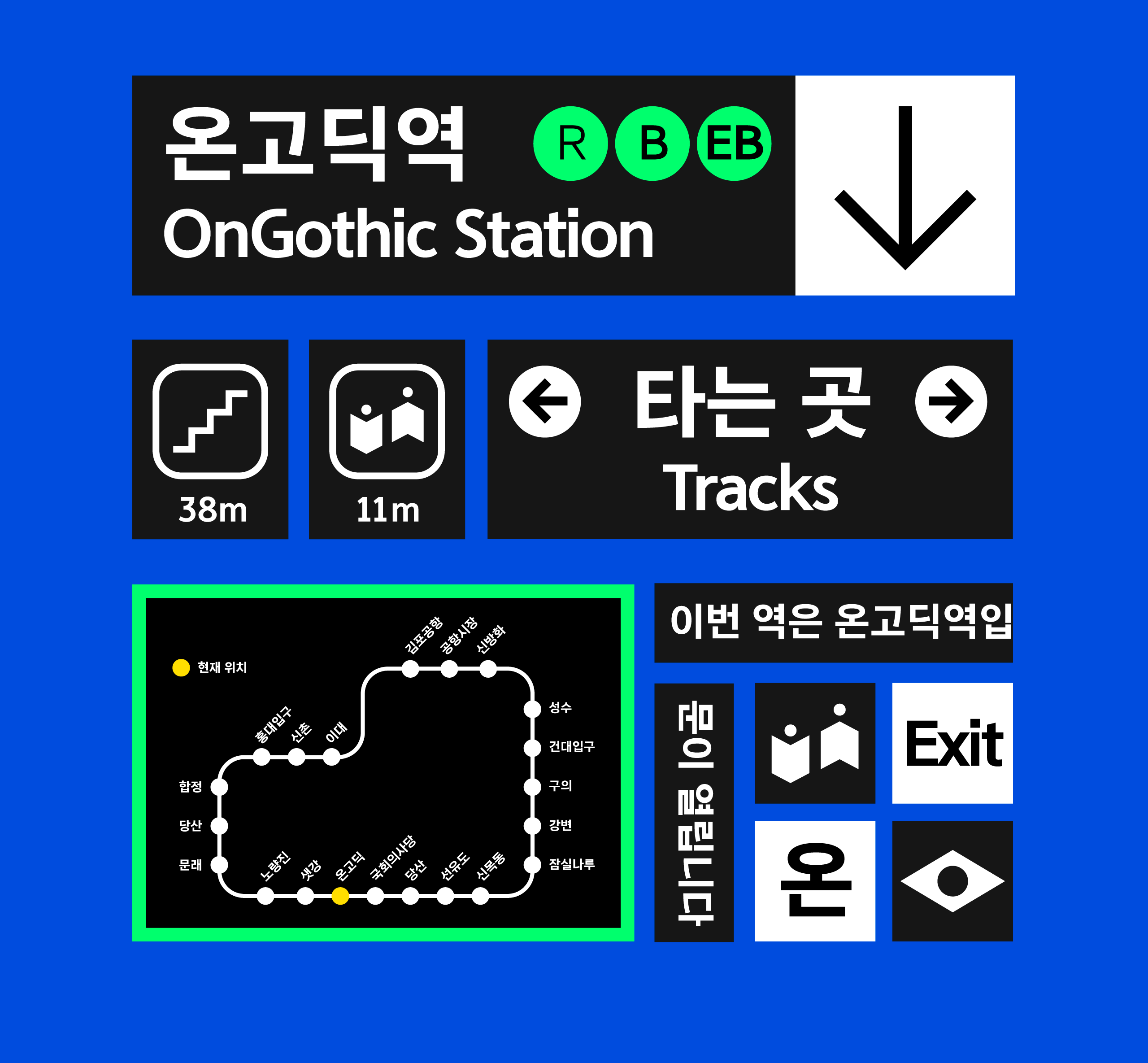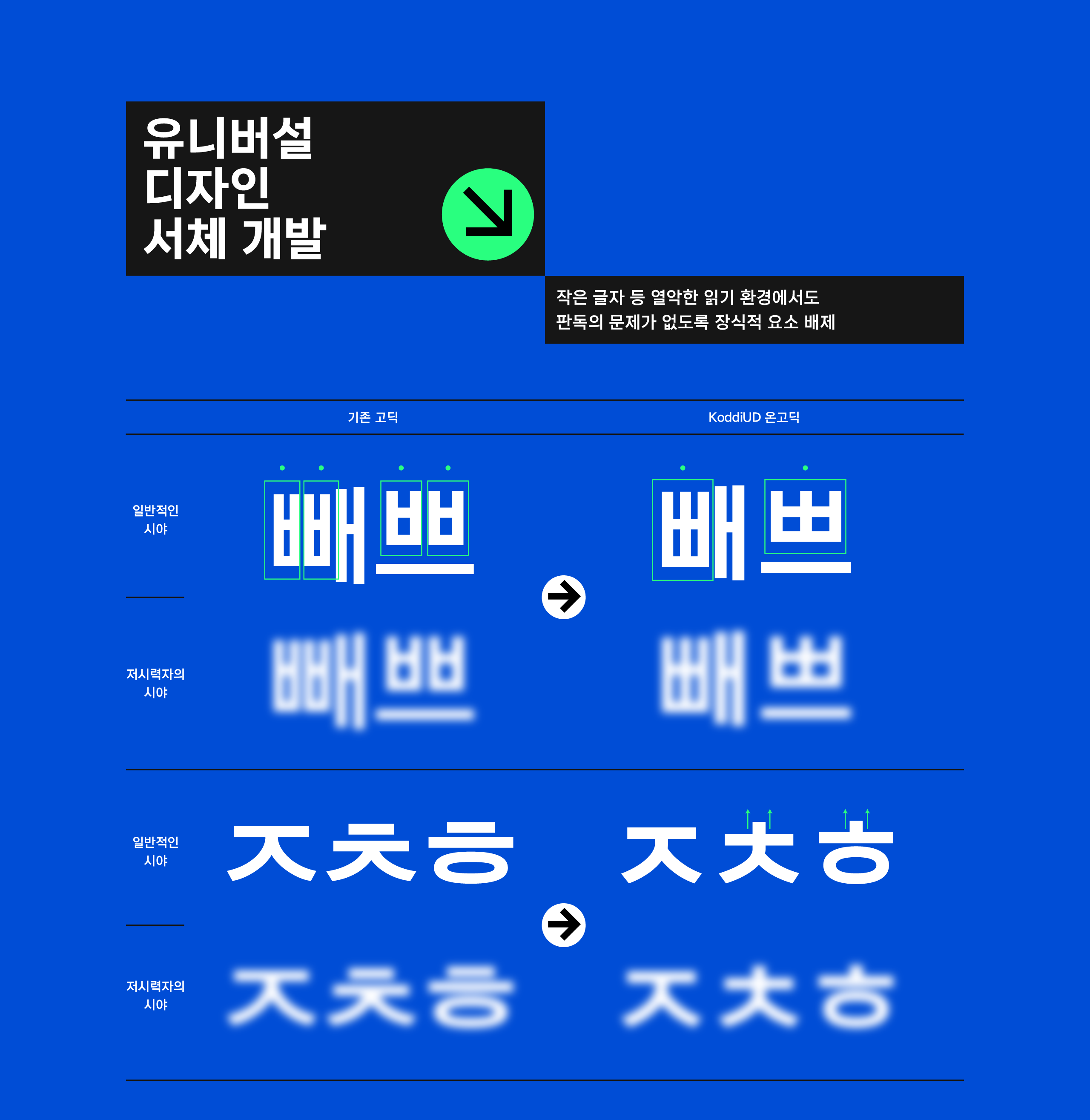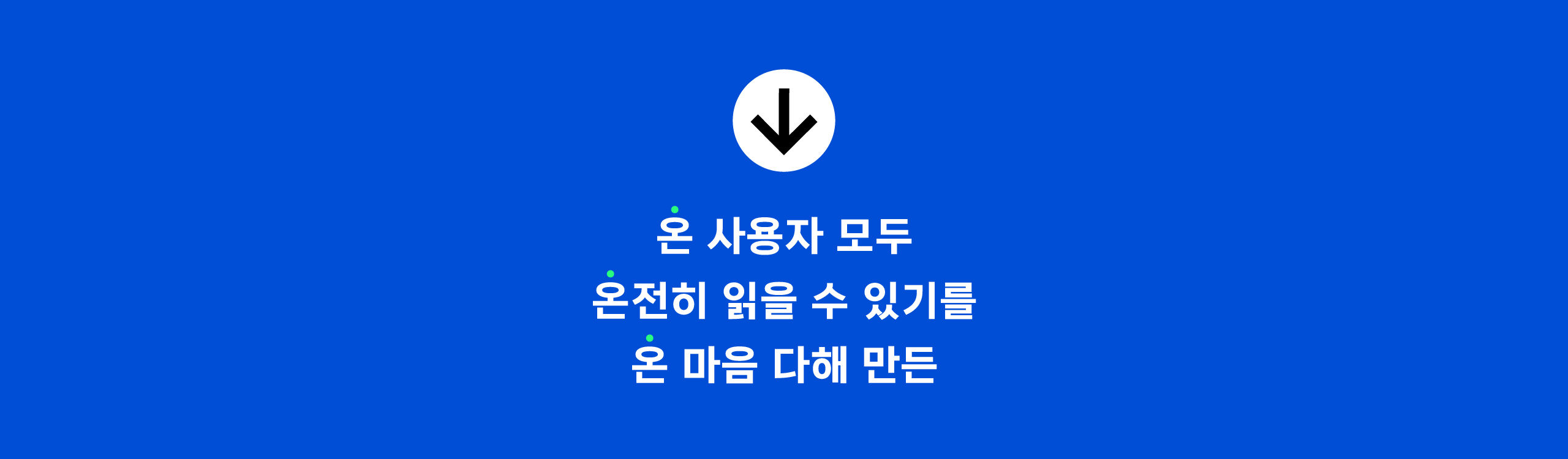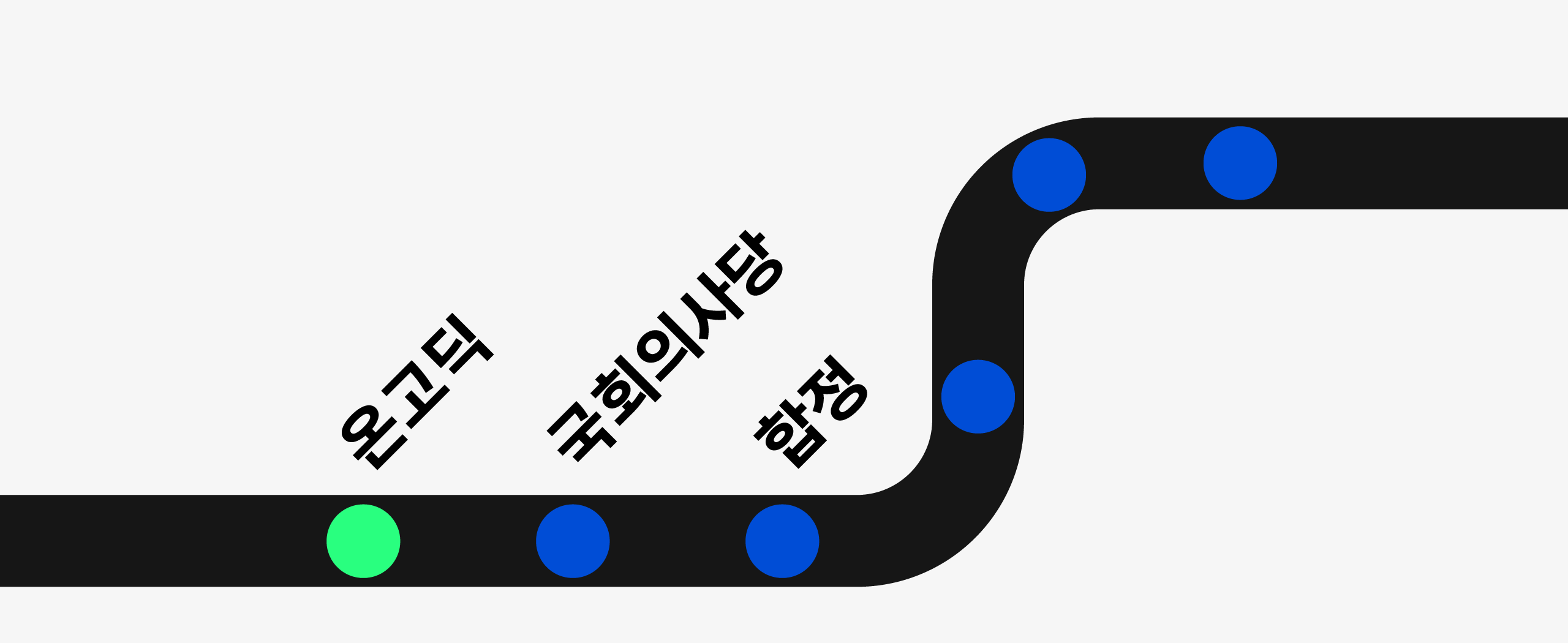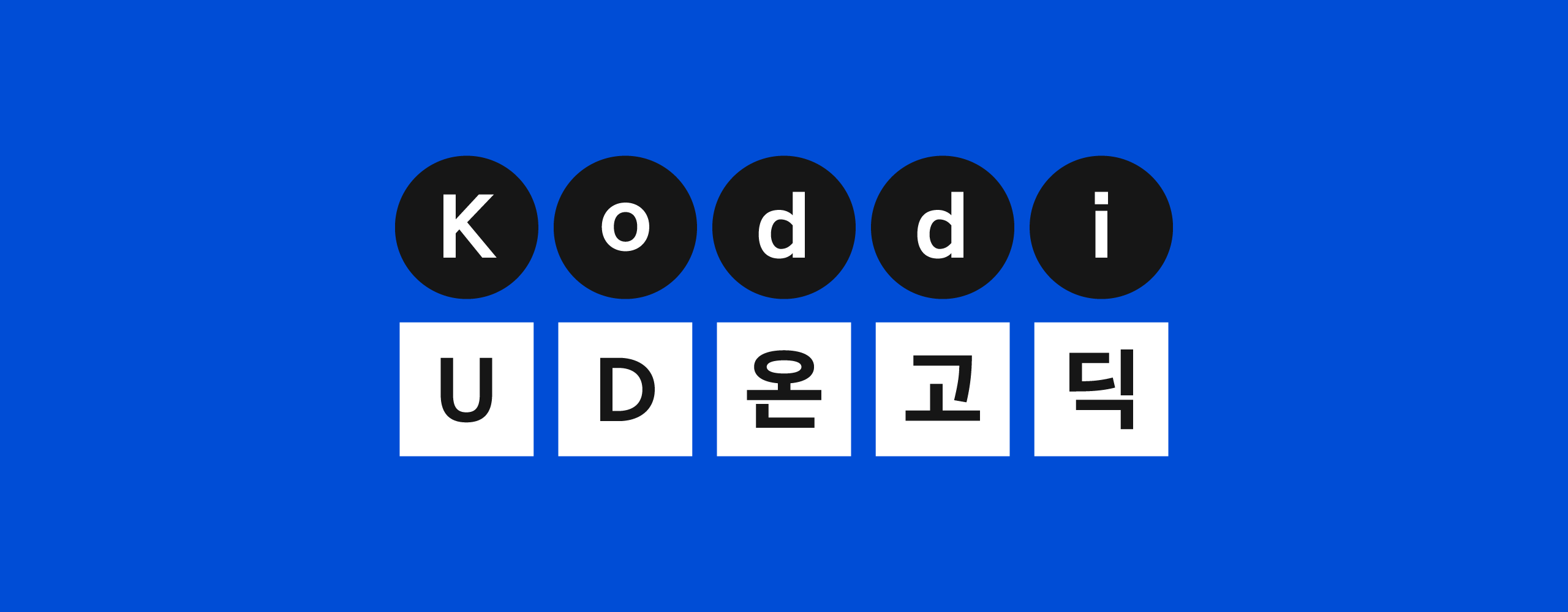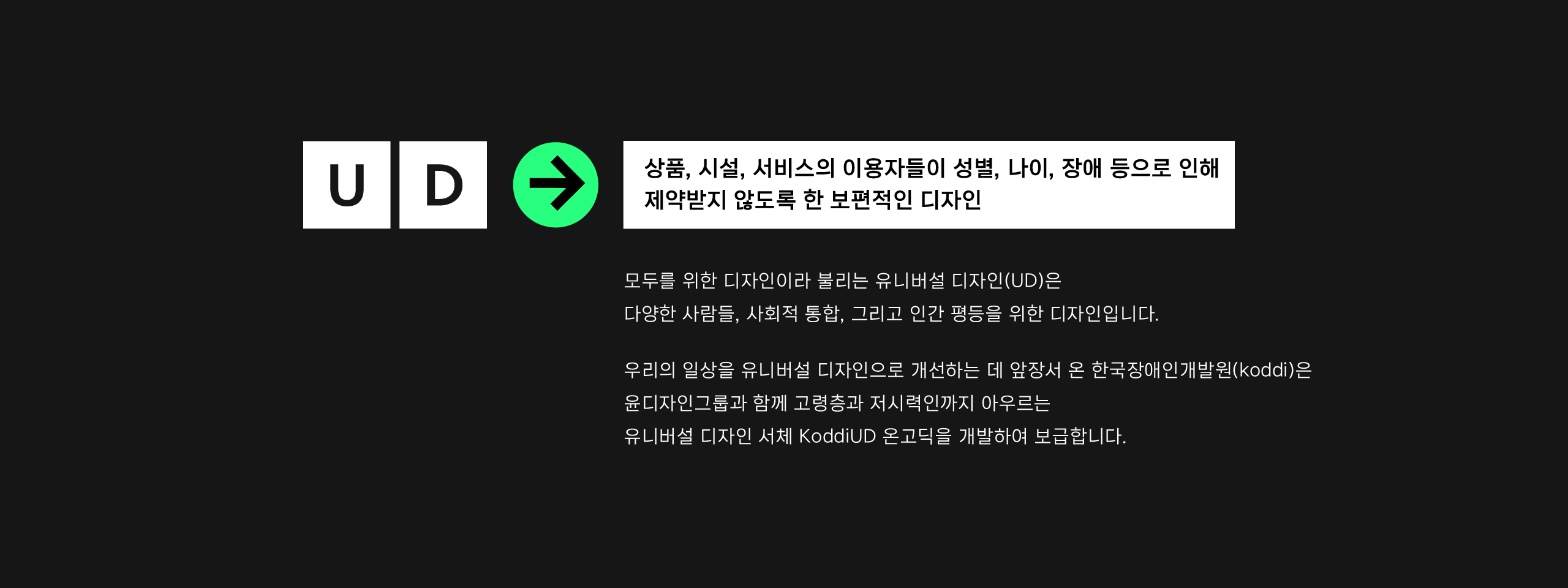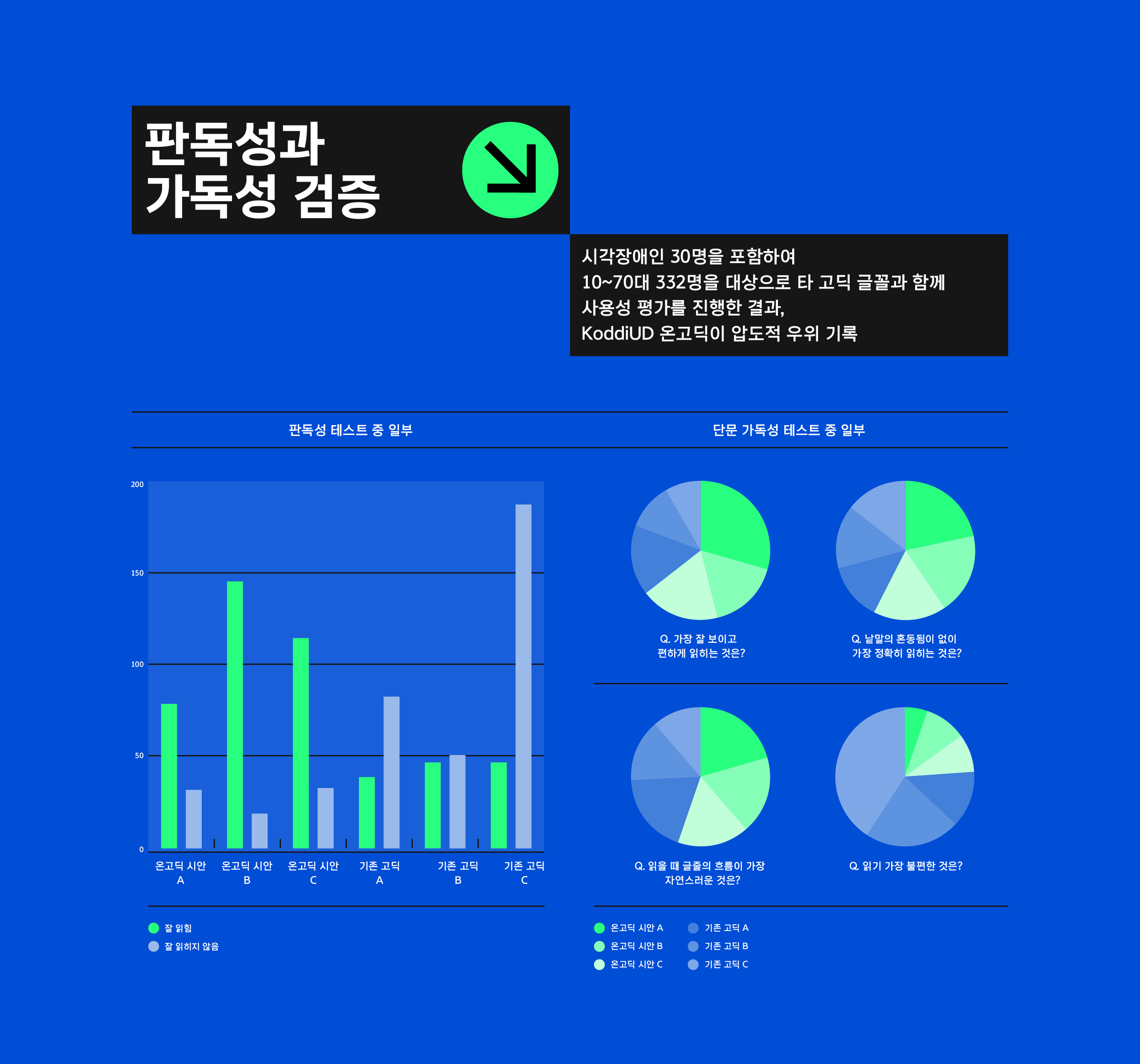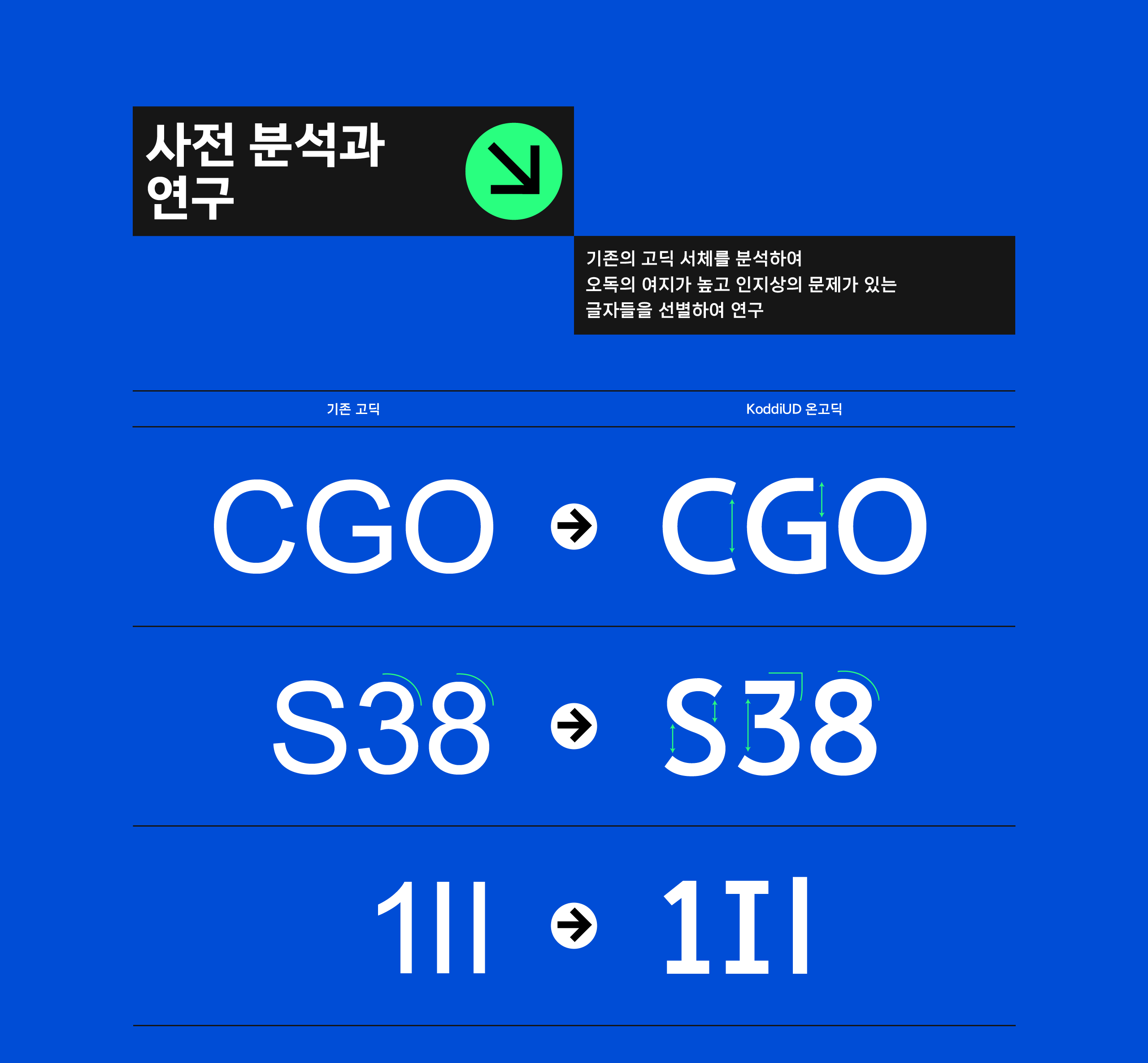
한국장애인개발원 [KoddiUD 온고딕]
KoddiUD 온고딕은 윤디자인그룹과 한국장애인개발원이 함께 개발한 유니버설 디자인 서체입니다. 고령층과 저시력인 등도 인지하기 쉽도록 만들어진 글꼴로서 기존의 고딕 서체를 분석하여 오독의 여지가 높고 인지상의 문제가 있는 글자들을 연구하여 작은 글자 등 열악한 글자 상황에서도 판독의 문제가 없도록 하였습니다. 개발 과정에서 시각장애인 30명을 포함한 10~70대 332명을 대상으로 타 고딕 글꼴과 함께 사용성 평가를 진행하여 판독성, 가독성의 우수함을 검증받았습니다.